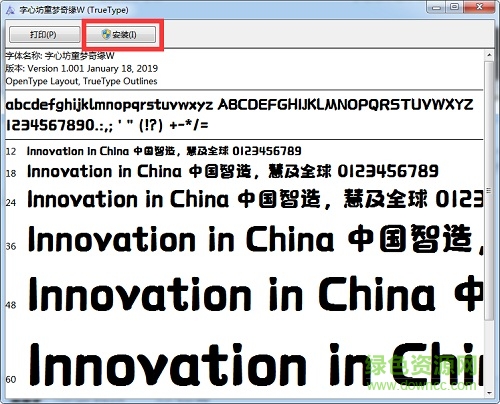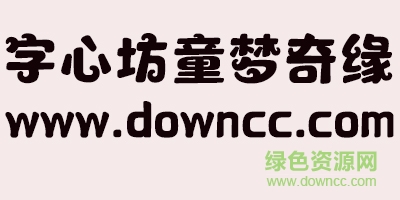
字心坊童夢奇緣是字心坊最新推出的字體。這款字體既可以用來設(shè)計卡通類也可以設(shè)計藝術(shù)類。字體外形是介于卡通字體和藝術(shù)字體之間。所以用途也是比較廣泛的!歡迎大家在綠色資源網(wǎng)下載使用。
字體融入夢境般的風(fēng)波卷元素,裝飾味十足,充滿童趣。以俏皮多變的線條,造就一款蘊含童真、童夢的字體。讓我們乘著童年的時光機(jī),進(jìn)入奇妙的夢幻之旅,遇見一場奇緣!
1.筆畫圓潤,有靈動的俏皮感
2.字體個性鮮明,字形特點時尚新穎,性格乖巧